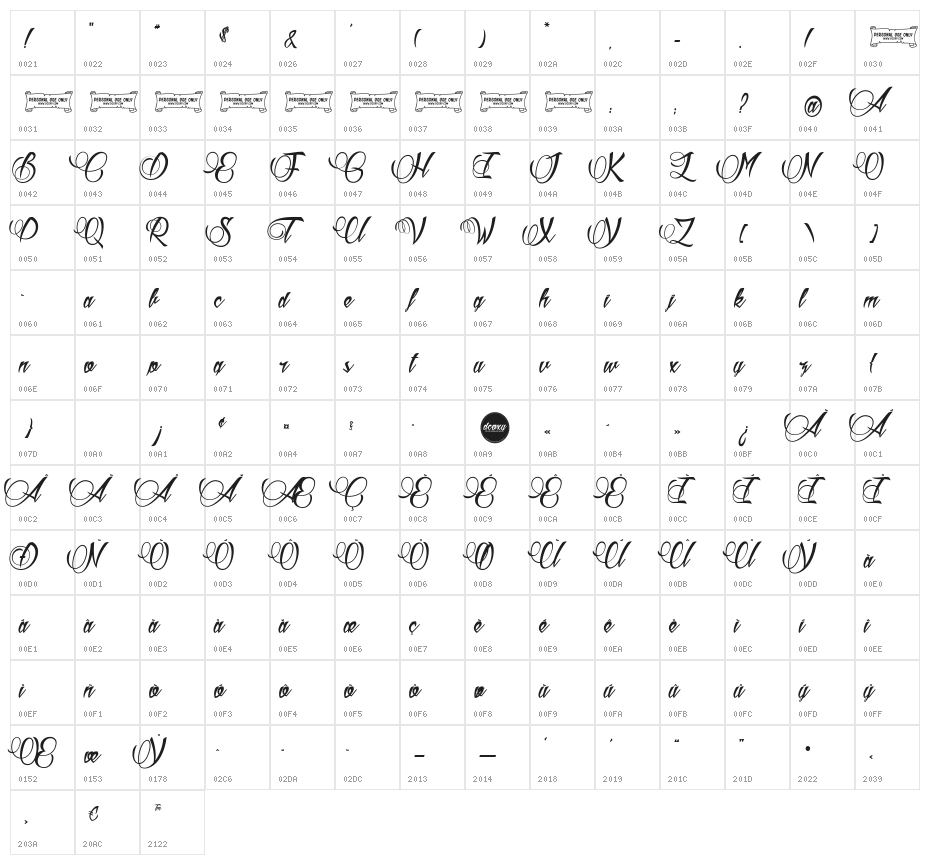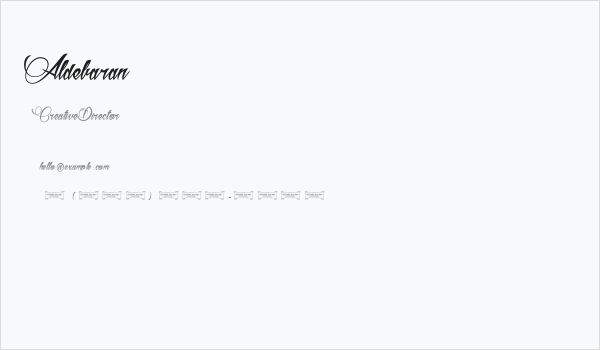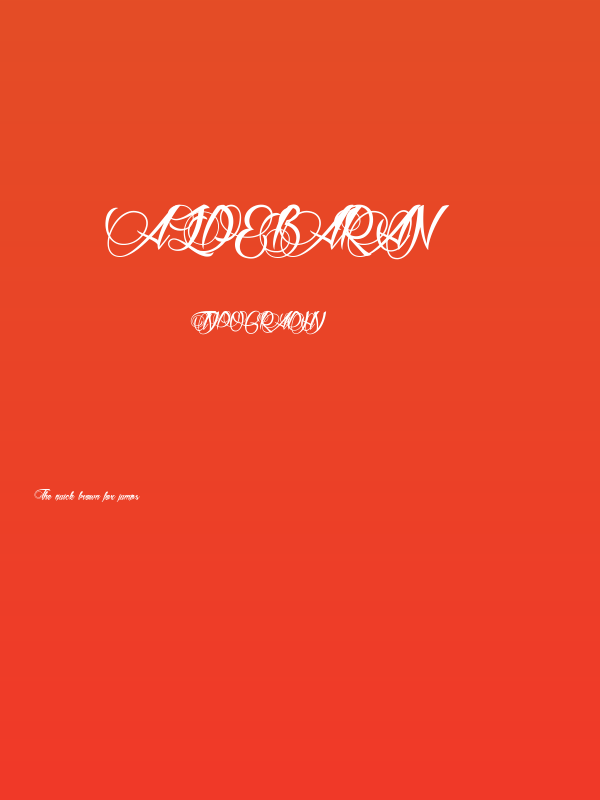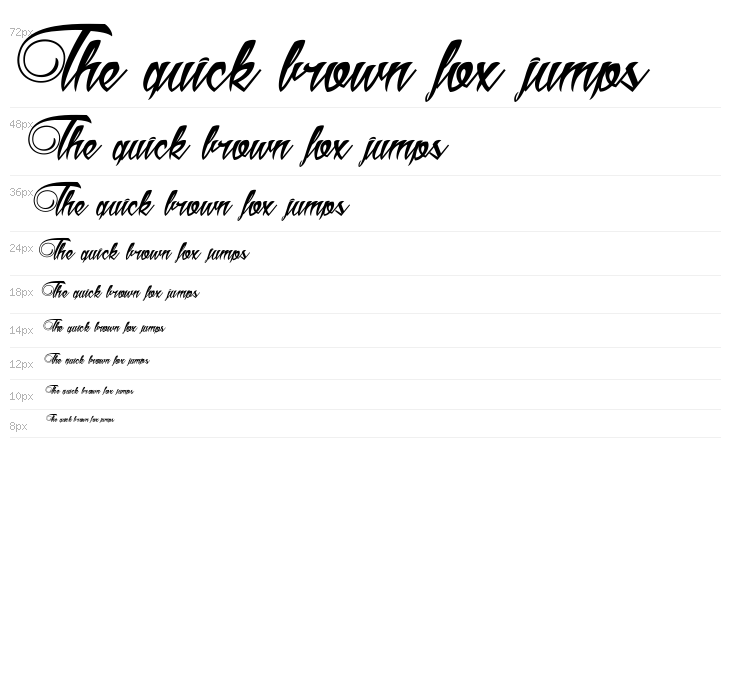
Aldebaran Font
✎ Script
| 分类 | Script |
| 斜体 | Yes |
| 整体风格 | Elegant, Formal |
| 使用场景 | Logos, Invitations, Branding |
| 推荐项目 | Ideal for wedding invitations, luxury branding, elegant logos, and formal event materials. |